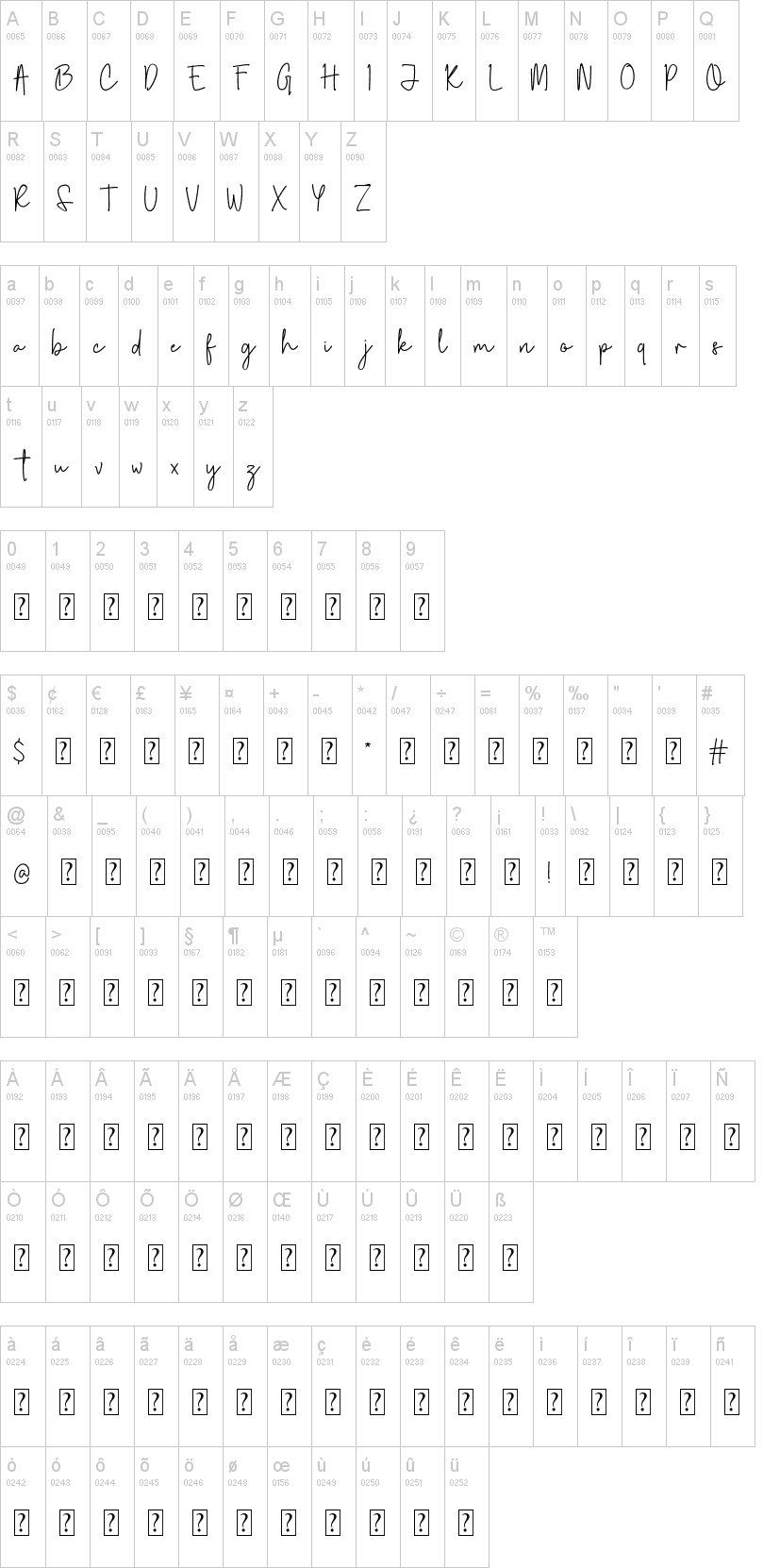
Jakarta Vise 是一种现代化的手写风格字体,其字体设计灵感来源于印度尼西亚首都雅加达的文化和风景。该字体由Alcode设计工作室开发,并于2018年发布。 Jakarta Vise 字体特点是具有流畅的曲线和手写感觉,同时也具有一定的艺术性和独特性。这种字体适用于许多不同的设计项目,例如:品牌标识、海报、贺卡、包装设计等。 该字体拥有多种字型和字重,包括粗体和斜体。此外,该字体还支持多种语言,包括拉丁文和西里尔文等。 如果您正在寻找一种具有现代感和手写风格的字体,那么 Jakarta Vise 可能是一个不错的选择。内容介绍
Jakarta Vise是一款非常不错的手写艺术字体,具有很好的视觉感,适合于文化类的宣传设计、商业类品牌的广告和产品包装设计以及个性化文字排版等较多场景。